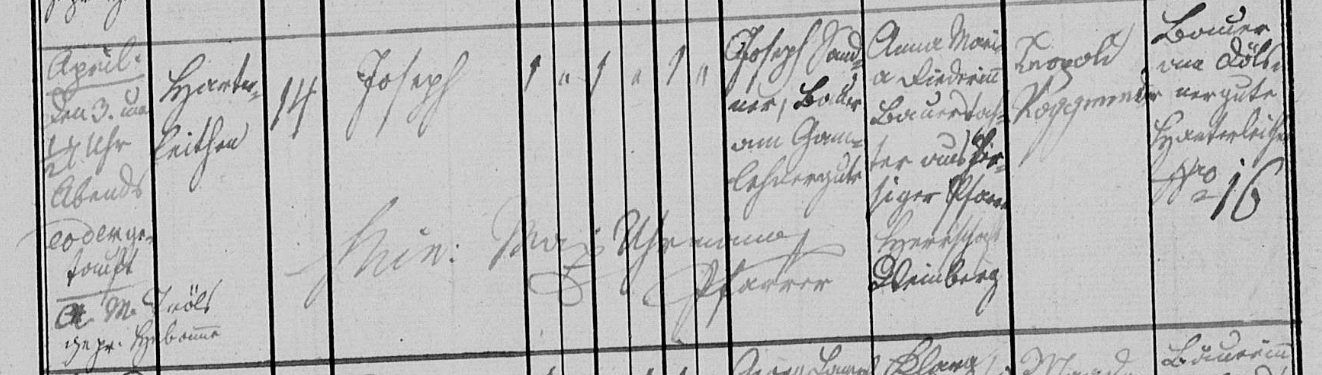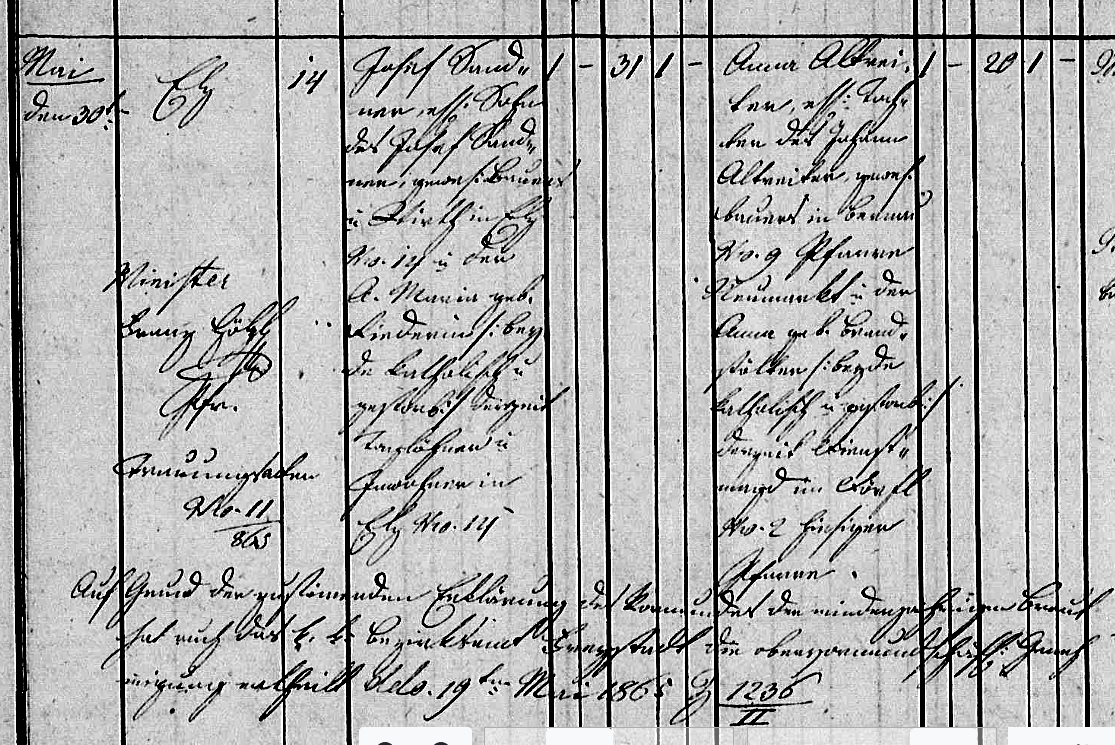
Auszug vom Kirchenbuch 1865 --> Oberösterreich, Kefermarkt
ich arbeite gerade an meiner Ahnenforschung und komme bei zwei Einträgen im Kirchenbuch von Kefermarkt (Oberösterreich) leider nicht mehr weiter. Es geht um eine Trauung aus dem Jahr 1865 sowie um einen möglichen Taufeintrag aus dem Jahr 1834.
Ich schaffe es leider nicht, den Text in den Matriken sauber zu lesen bzw. korrekt zu übersetzen — vor allem bin ich unsicher, ob es sich bei beiden Einträgen wirklich um dieselbe Person handelt oder ob ich hier einen Fehler in meiner Linie habe.
1️⃣ Trauungseintrag (Kefermarkt, 1865)
2️⃣ Möglicher Taufeintrag (Kefermarkt, 1834)
Meine Frage ist:
→ Gehören diese beiden Einträge zur gleichen Person, oder verwechsle ich hier jemanden?
Es gibt zwar ein paar unsichere Lesarten. Der Schluss liegt aber dennoch nahe, dass es sich um ein und dieselbe Person handelt.
Im Taufeintrag zum kleinen Joseph werden als Eltern vermerkt: Joseph Sandner, Bauer am Gamlehnergute | Anna Maria a Diederius, Bauerntochter aus hiesiger Pfarre, Herrschaft Weinberg
Im Trauungsverzeichnis tauchen dieselben Angaben auf: Josef Sandner, ehl. Sohn des Josef Sandner, gewes. Bauer und Wirth in Elz Nro. 14 und der A. Maria geb. Diederius | beyde katholisch und gestorb. | derzeit Taglöhner und Inwohner in Elz Nro. 14
Als Alter des Bräutigams ist wie zu erwarten 31 angegeben.
Gestolpert bin ich vor allem über den Mädchennamen der Mutter, Diederius. Das ist jedenfalls meine spontane Lesart. Die lateinische Endung wirkt aber ungewöhnlich. Vielleicht hast du weitere Informationen, die Licht ins Dunkel bringen.
Liegt natürlich nahe. Ich sehe aber nichts, was einem ch ähnelt. Und im Taufeintrag sieht es so aus, als hätte das u am Ende einen Strich darüber – wie man es von abgekürzten lateinischen Wörtern kennt. Vielleicht hatte der Schreiber einen Hang zum Lateinischen, deshalb auch "a" für "geb.", was wohl für "[nat]a" steht (vermute ich zumindest).
Ich habe inzwischen noch ein paar zusätzliche Hinweise gefunden und bin mir jetzt besonders unsicher wegen des Nachnamens der Anna Maria.
Im Trauungseintrag von 1865 lese ich den Namen der Braut als
Anna Maria Diederich – bin mir aber nicht sicher, ob der Name eventuell auch als „Riederin“ zu lesen sein könnte. Vielleicht interpretiere ich die Schrift falsch.
Im möglichen Taufeintrag von 1834 scheint der Name sehr ähnlich zu sein, daher hoffe ich, dass es sich wirklich um dieselbe Person handelt. Falls jemand die Schrift besser lesen kann, wäre ich sehr dankbar, wenn ihr mir sagen könntet, ob die beiden Einträge zueinander passen.
Zusätzlich habe ich noch zwei Sterbeeinträge gefunden, die vermutlich zur gleichen Familie gehören:
Leider kann ich die Texte auch hier nicht vollständig und korrekt entziffern.
Ich habe mir mal andere Einträge aus derselben Zeit angeschaut. Ich bin nun ziemlich sicher, dass es tatsächlich Riederin heißen muss. Eindeutig mit R beginnende Namen haben denselben Anstrich und Schwung (den ich fälschlich für ein D gehalten habe). Weibliche Nachnamen werden immer in der weiblichen Form angegeben: -in am Ende. Aus den Jahren 1810 und 1813 gibt es Taufeinträge zu den Eltern Joseph Sandner und Anna Maria Riederin, wobei der Name der Mutter in lat. Buchstaben geschrieben ist und damit leichter zu entziffern. Ich glaube, damit ist die Namensfrage geklärt. (Die Identität der Personen in den beiden Einträgen hielt ich auch vorher schon für gesichert.)